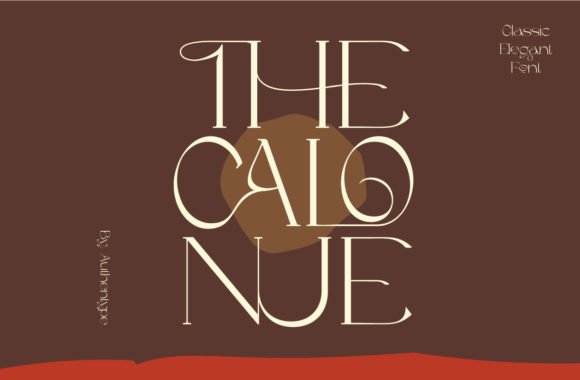
Creativefabrica The Calonue Font 2021
[Creativefabrica] The Calonue Font (2021)
Calonue - это классический и элегантный шрифт с засечками, с великолепными символами и скорописью.
Добавьте его к своим самым креативным идеям и обратите внимание, как он их выделяет!